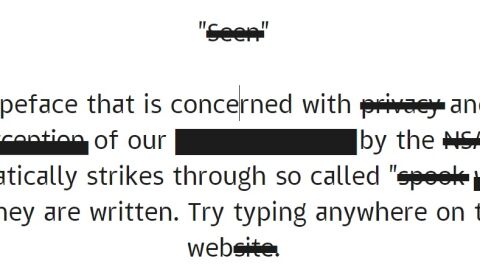
La tipografía que camufla las palabras más buscadas por los espías de la NSA
El diseñador Emil Kozole ha desarrollado una herramienta para camuflar las palabras que buscan durante sus rastreos de internet las agencias de seguridad internacionales. Cada que vez que escribamos “policía”, “Nike”, “Anonymous” o “anthrax”, la tipografía Seen ("visto", en inglés) se encargará de ponerle las cosas difíciles a los espías para que no sospechen de nosotros. Con ello, Kozole pretende concienciar a los ciudadanos para que sepan hasta dónde puede llegar la cibervigilancia.
Seamos o no conscientes, cada paso que damos en la Red deja una huella. De hecho, hasta el más simple e inofensivo mensaje en Facebook o Twitter puede despertar ciertas suspicacias entre los agentes de la Agencia Nacional de Seguridad de Estados Unidos si contiene alguna palabra que les pueda parecer sospechosa. Sin darnos cuenta, podemos meter la pata, así que para evitar algún susto que otro Emil Kozole propone una alternativa.
En lugar de prestar atención a todo aquello que escribamos para no utilizar ninguna de las cerca de 30.000 palabras que los espías estadounidenses rastrean en busca de conductas peligrosas, este diseñador ofrece una tipografía que detecta esas palabras y las tacha. No nos avisa si hemos incluido en nuestro texto tal o cual nombre propio o ciertas siglas que puedan hacer saltar las alarmas: la fuente Seen simplemente se encarga de poner una línea negra sobre el término para complicar la tarea a los agentes de la NSA.
Se trata, eso sí, de un experimento. Que nadie caiga en el error de pensar que Emil Kozole ha creado esta tipografía para echar un cable a los que sí tienen la firme intención de cometer algún delito. Su propósito no es otro que hacernos reflexionar sobre los límites de la libertad de expresión en internet y hasta dónde estamos coartados por las autoridades. Tal y como él mismo explica, se trata de que "la gente vea y se pregunte por qué algunas de las palabras están en la lista y por qué otras no lo están".
Para conseguirlo, este diseñador esloveno nos propone descargar su fuente, instalarla en nuestro ordenador y probarla. Basta con añadirla a la carpeta de tipografías que se puede emplear en Windows o Macintosh en programas como Word, Illustrator o InDesign, y comprobar de primera mano qué palabras tacha, cuáles subrraya y cuáles emborrona.
Para dejar constancia de qué palabras entrañan mayor riesgo a ojos de los espías, Kozole ha incorporado esas tres formas distintas de indicar que el término que empleamos es tabú. En función del grado de riesgo que pueda denotar su uso, la tipografía Seen las marcará de una u otra forma para ocultar más o menos la palabra.
Por ejemplo, si ponemos “información”, veremos que simplemente la tacha. Si nos atrevemos a utilizar “Guantánamo”, más peliaguda, veremos que la subraya y que, además, resulta más complicado ver qué se oculta tras esa franja negra. Por último, si nos la jugamos con “presidente”, este tipo de letra colocará sobre ella un borrón para que nadie pueda saber qué palabra hay ahí.
Esta idea surgió allá por 2013 cuando Edward Snowden comenzó a filtrar una serie de documentos secretos de las agencias de seguridad de Estados Unidos, en los que se explicaba cómo se las ingeniaban para espiar a ciudadanos de todo el mundo. Esta circunstancia llevó a Kozole a poner en marchar el proyecto Seen y presentarlo en el máster en diseño y comunicación que estaba cursando en la universidad de arte londinense Central Saint Martins.
Este intrépido creador quedó tan asombrado con las revelaciones del exanalista de la NSA que recabó la información necesaria para acabar descubriendo que no solo se trataba de las palabras que monitoriza la agencia de seguridad de Estados Unidos, sino que esta práctica también la empleaban otras agencias internacionales. Según sus investigaciones, el Cuartel General de Comunicaciones del Gobierno británico tiene en su listado hasta 40.000 palabras cuyo uso podría despertar ciertos recelos.
Utilizar palabras tan aparentemente inofensivas como “alcachofa”, “clon”, “banco”, “Harvard” o “ternera” podría meternos en un lío. Además, como apunta Emil Kozole, estas listas no dejan nunca de crecer. Desde que fuera filtrada la información dos años atrás, el registro ha ido sumando nuevos términos que, obviamente, nadie conoce más allá de los agentes que trabajan en estos servicios de inteligencia.
Como él mismo reconoce, aún no se ha puesto en contacto con la NSA para presentarle su proyecto. No sabemos si por miedo a que tomen represalias contra él o porque (como muchos pensamos) teme que su tipografía no pase de ser más que un chiste con el que los espías amenicen sus reuniones.